邯郸(元)赵孟頫千字文这字体外貌圆润而筋骨内涵,其点画华滋遒劲,结体宽绰秀美,点画之间彼此呼应十分紧密。
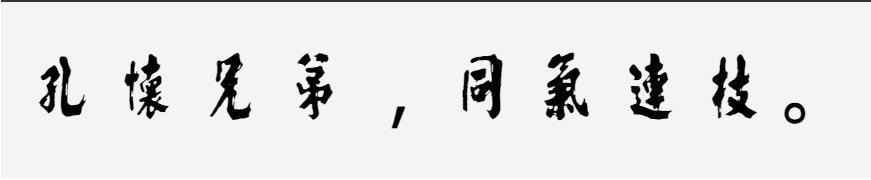
邯郸(宋)朱熹榜书千字文下笔稳健,笔锋隐忍有力,笔墨精妙,洒脱自然。
邯郸(宋)苏东坡千字文这款字体用墨丰腴,结字扁平,左低右高,笔画恣意,落字错落,率意天真。
邯郸(清)张謇行书千字文行笔从容稳健,骨干平正,收放有度,不激不燥,有珠华玉润之象。